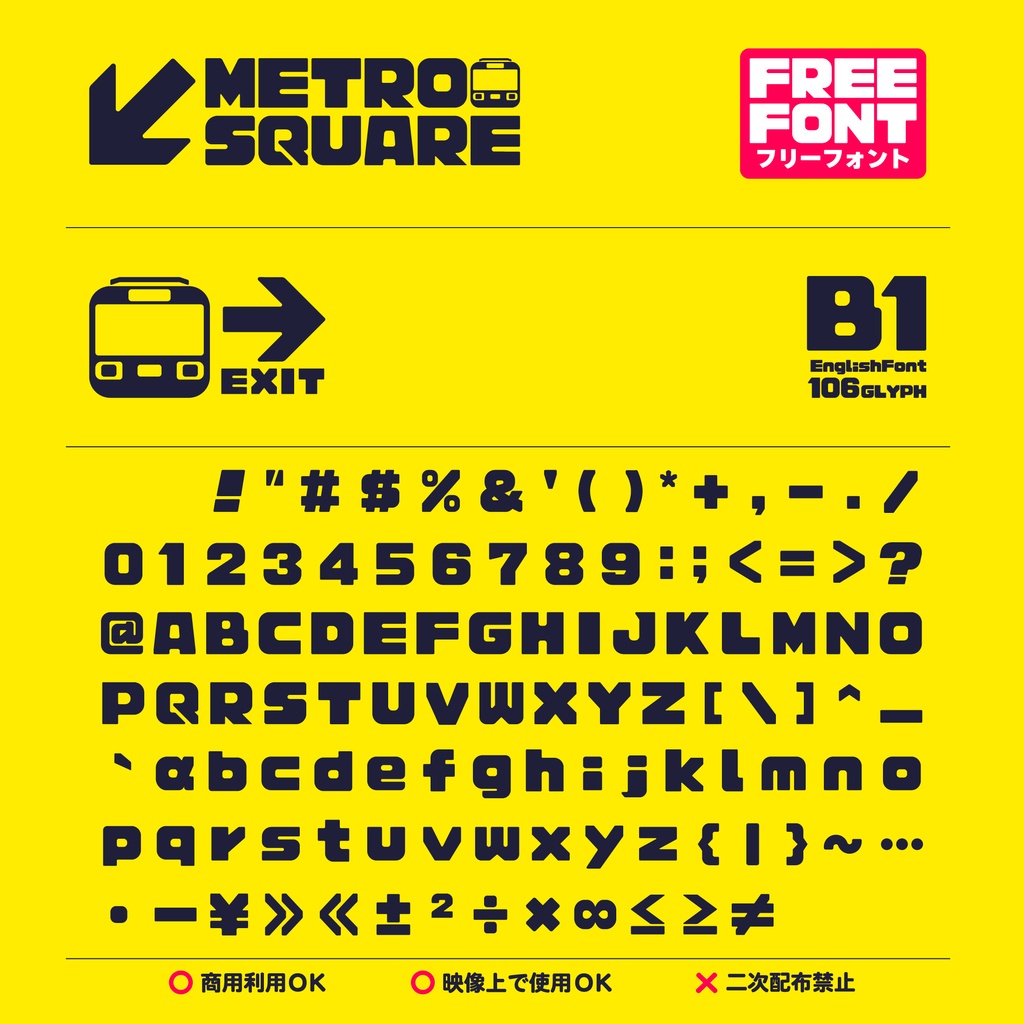
フリーフォント[MetroSquare]1.0_FONT
カーニングを簡単にそしてコンパクトに収められる為に作られた、 都市地下鉄を意匠としたフォントです。 オタクコンテンツなどに使われると作者は喜びます。 ● [Metro Square]fontはフリーフォント ● [Metro Square Stella]fontは有料版です。 FONTTYPE:OpenType ----------------------------------------------------------- 当フォントは仕様変更などのバージョンアップすることがあります。 更新やリリースなどのインフォメーションとして ▶ https://twitter.com/OtoroesakiWorks にて 更新情報などを発信しております。 ----------------------------------------------------------- このフォントはAdobe Illustrator2025と 武蔵システム(http://opentype.jp)のOTEditを使って作成しました ----------------------------------------------------------- ■ 免責事項 ■ 本フォントデータの使用に関連して、購入者の直接、及び間接的に生ずる一切の損害および第三者からなされる請求について一切責任を負担しません。 ■ 禁止事項 ■ サーバー等にアップロードして送信可能とする目的の使用は出来ません。 データの改変、販売、頒布、バックアップ目的以外のコピーは許可しておりません。 データを使用して作成した成果物の著作権登録、意匠登録および商標登録などの知的財産権の登録を行うことは許可されていません。